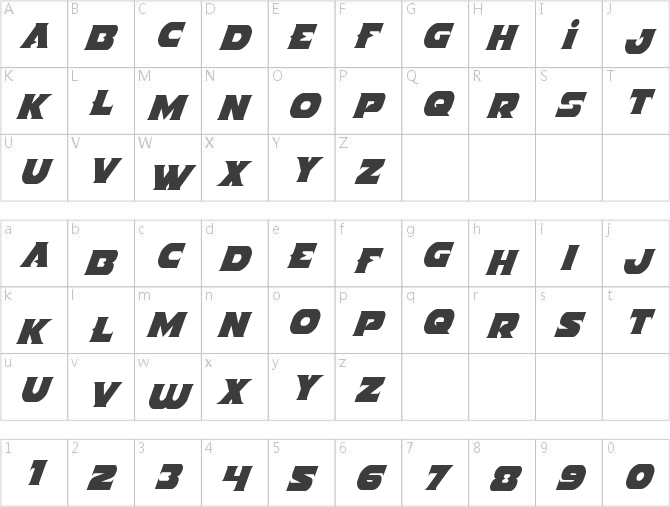
字体名称: indigod
indigodemoncondital
indigodemoncondital介绍
indigodemoncondital字体字库是一款让人赏心悦目、百看不厌的英文字体,适合各类广告和产品包装设计应用,字体大小0.04MB,格式为ttf字体,上传用户是诚泽永信,作者/版权方为未知